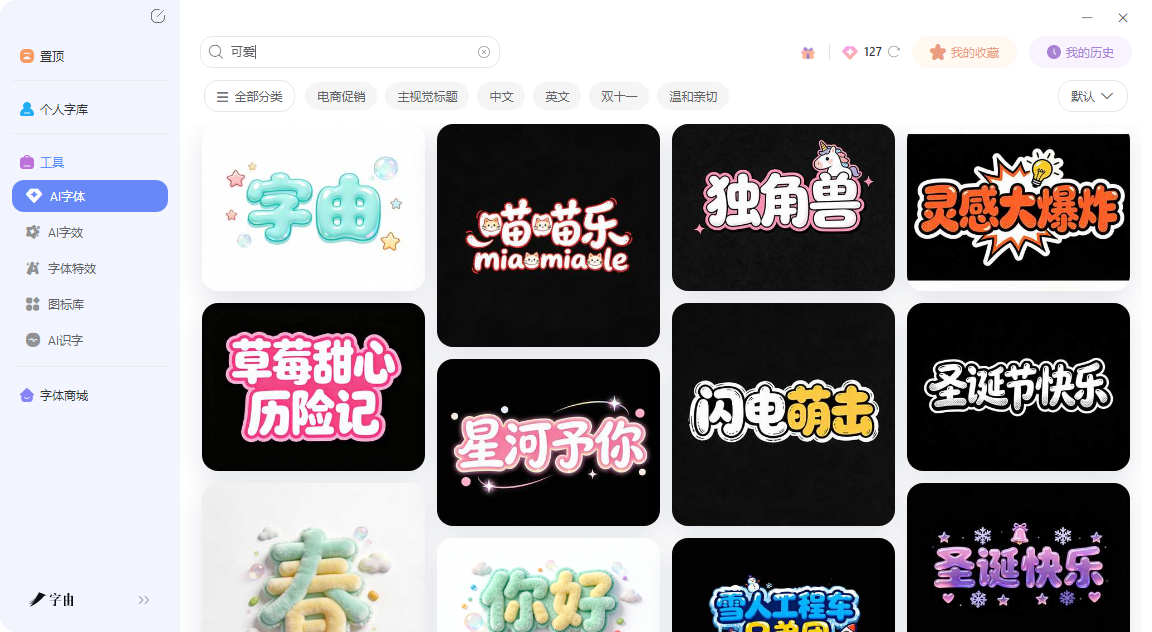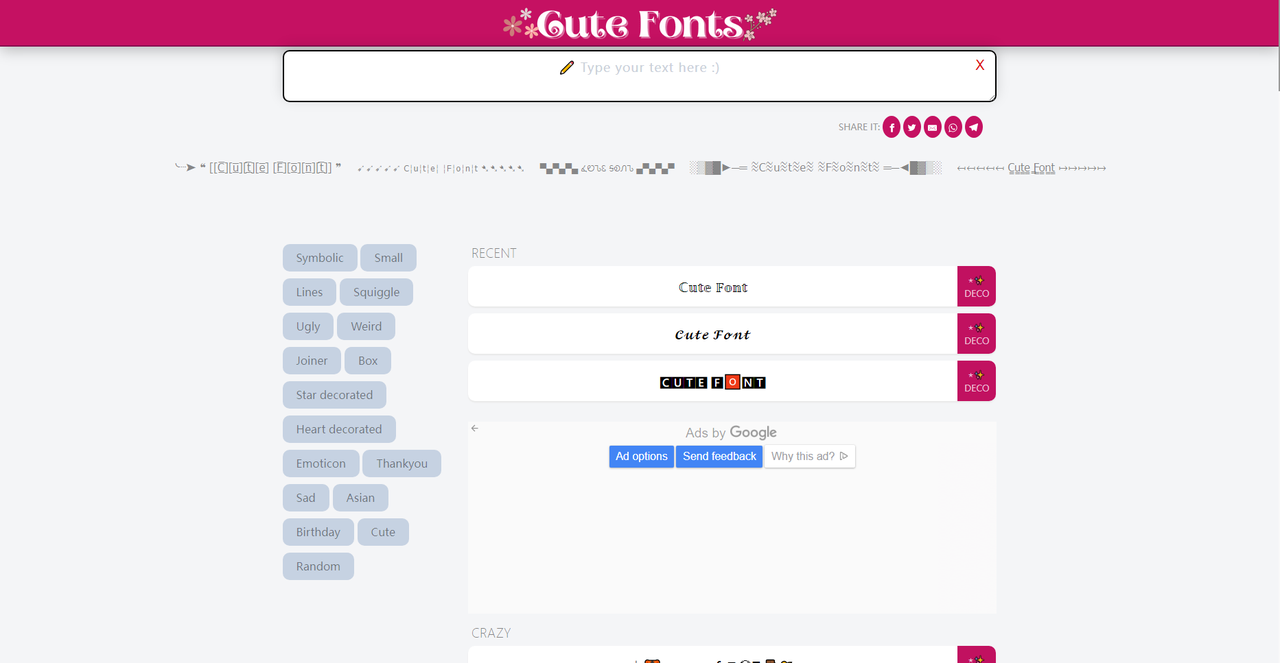
设计不够出彩?试试这些俏皮可爱的女生字体
做手账的时候,想给今天的心情配一行软萌的标题;给闺蜜做生日贺卡,希望名字带点少女心的装饰;设计甜品店菜单,字体要甜但不能腻。这些场景下,系统自带的黑体宋体是完全排不上用场的,这时候就需要专门做可爱风格的字体资源,从圆滚滚的手写体到带爱心、星星装饰的花体,从日系kawaii到软萌卡通。今天我就为大家整理了6个可爱女生字体相关的网站,有在线生成器、有下载站、有灵感合集,总有一款是你喜欢的。
做可爱风格设计,最常用的字体类型无非就那几样:圆体(拐角圆润)、手写体(有温度)、卡通体(带装饰)。字由的字体库里这三类加起来上百款,而且全都可以一键激活。打开字由客户端,在左侧“字体类型”筛选栏里,你可以同时勾选“圆体”“手写体”“创意字体”——这三个分类里藏着大量适合可爱风格的字体。比如“字由芳华体”,笔画纤细带连笔,像用彩色水笔写出来的,做手账标题特别出片;还有“点字青花楷”,虽然是楷书但圆润可爱,适合中式风格的可爱设计。
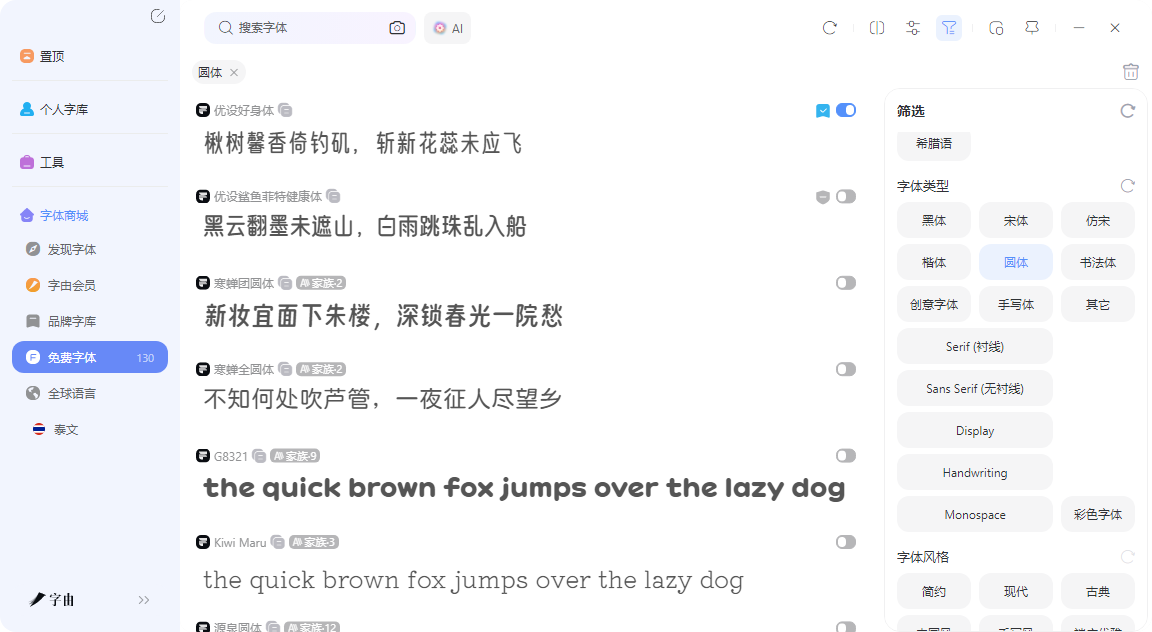
除此之外你也可以选择用字由的AI字体功能来生成图片模板,操作过程也十分简单,只需要点进【AI工具】,再搜索框里搜索“可爱”“粉色”等关键词,就可以出来很多类型丰富的、已经自己调好样式的AI字体模板,你只需要在文字框里填入你想要的文字,再等待几十秒就可以拥有现成的可爱的字体图片了,并且你也可以选择放在各种设计软件里,十分方便。
2、Gute Fonts
第二个网站叫Gute Fonts。它的界面很简洁:顶部一个输入框,输入文字后,下面会生成多种装饰风格的字体样式。其中最符合“可爱女生字体”需求的是“Heart decorated”(爱心装饰)和“Star decorated”(星星装饰)——每个字母周围会加上小心心或小星星,生成出来的文字像贴纸一样。还有“Cute Font”本身就是一个自带圆润感的样式。这个工具生成的是Unicode字符,不是图片。所以你选中喜欢的样式,点一下旁边的复制按钮,就能直接粘贴到微信朋友圈、抖音简介、小红书文案、游戏昵称里。不需要下载任何软件,打开网页就能用。如果你只是想偶尔给社交账号加点可爱元素,Gute Fonts比装字体快多了。
3、Cute Font Generator
第三个工具叫Cute Font Generator。从截图看,它主打“kawaii vibes”(可爱氛围),生成的文字会自带emoji装饰,比如🎨✨🕶️等。而且它提供了多种分类:Bold、Aesthetic、Cursive、Cute、Instagram等,每种分类下面又有若干样式。使用方式和上一个类似:输入文字,选择样式,复制粘贴。适合在Instagram、Discord、TikTok等社交平台上用可爱字体写简介、标题或评论区留言。这个工具的亮点是“随机”功能——你不太确定想要什么风格的时候,点一下随机,它会自动帮你组合一种样式,有时候能撞到意想不到的效果。
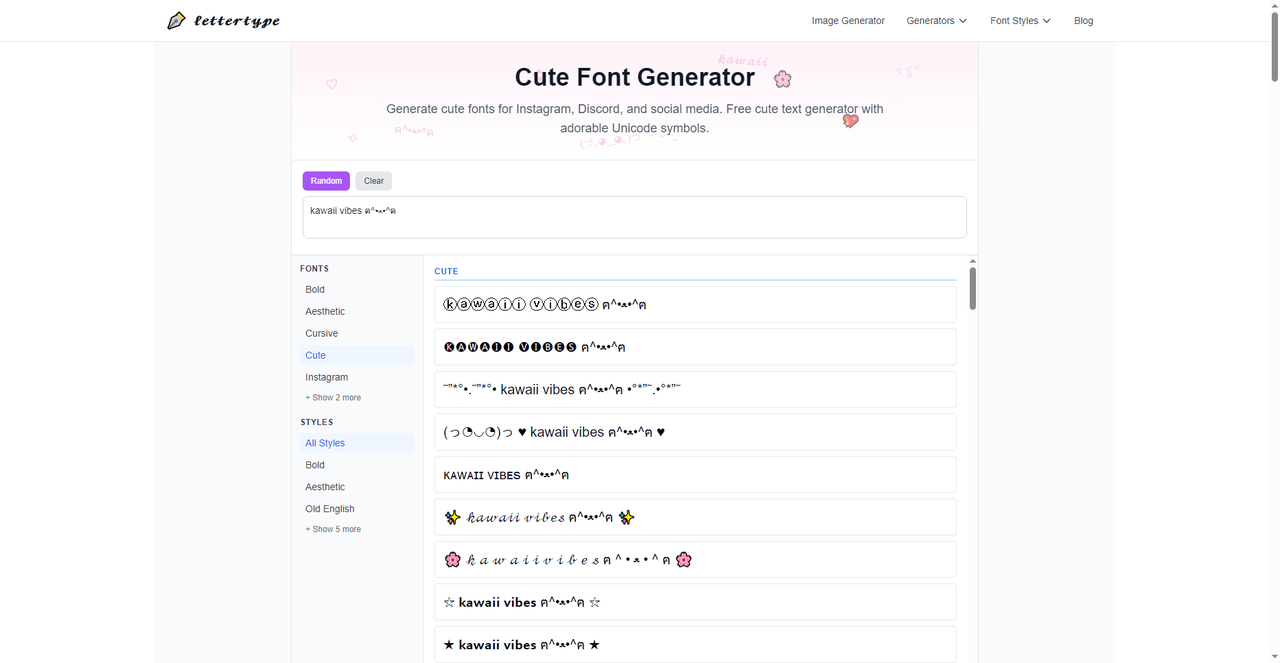
4、Kawaii Fonts
第四个网站叫Kawaii Fonts。这是一个专门收集日系可爱字体的下载站,标题写着“39 free fonts”,收录了Kinkee、Billo、Kitten(5种样式)、Cupid de Locke、Cookies等字体。每款都有预览图,展示了字母和简单单词的效果。“Kawaii”是日语的“可爱”,这类字体通常笔画圆润、带点手绘感,有的还会在字母上加小圆点或者小尾巴。截图中“Kitten”字体的预览写的是“Kitten Bold Regular AaBbCcDdEeFf”,看起来是软萌的猫主题字体;“Cookies”像饼干一样圆圆胖胖的。
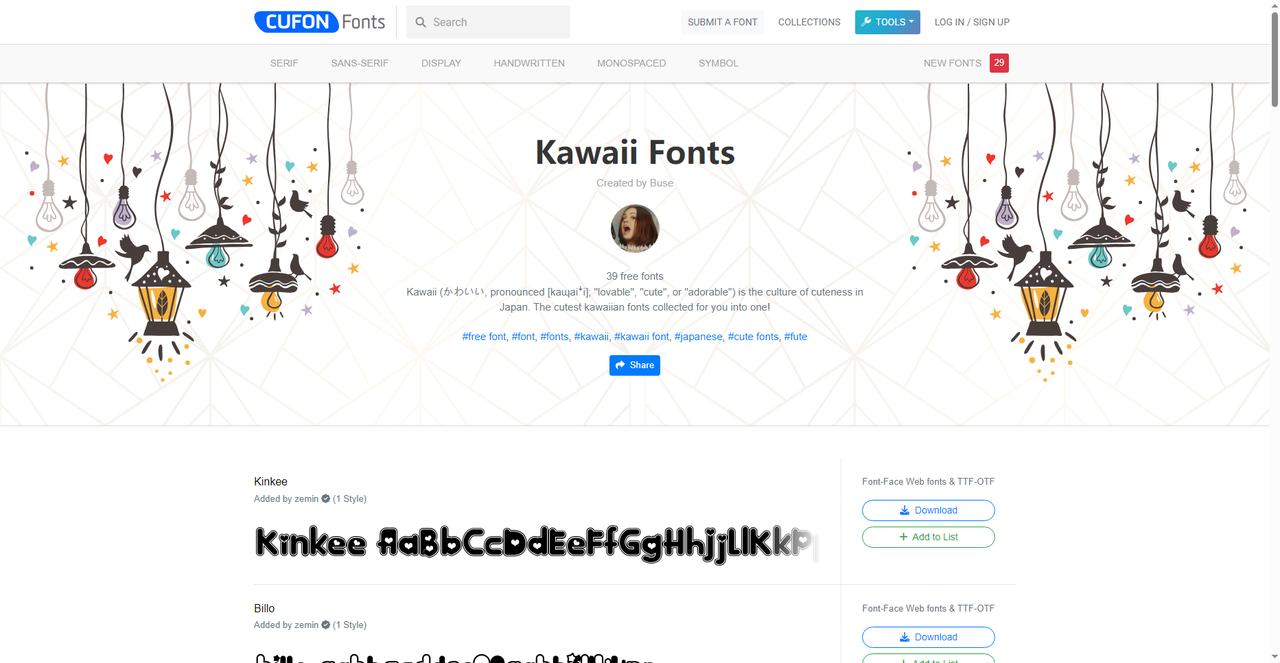
5、cutefonts
第五个网站是CuteFonts.org。从截图看,它提供了多种装饰风格的字体预览,分类详细。它的核心功能是“CUTE & PRETTY TEXT GENERATOR”——输入文字后,下面会列出各种样式的预览,每个样式旁边有“SHARE IT”按钮,可以直接复制或分享。样式包括Cursive Font(草书)、Super Bend(超级弯曲)、Double Struck(双线体)、Medieval Font(中世纪)、EmojiFont(表情符号字体)、Tribal Font、Old English等。这个站的装饰风格更偏“花哨”——有的样式会在字母周围加框、加符号,适合做派对邀请函、社交媒体配图、或者需要强烈视觉效果的标题。
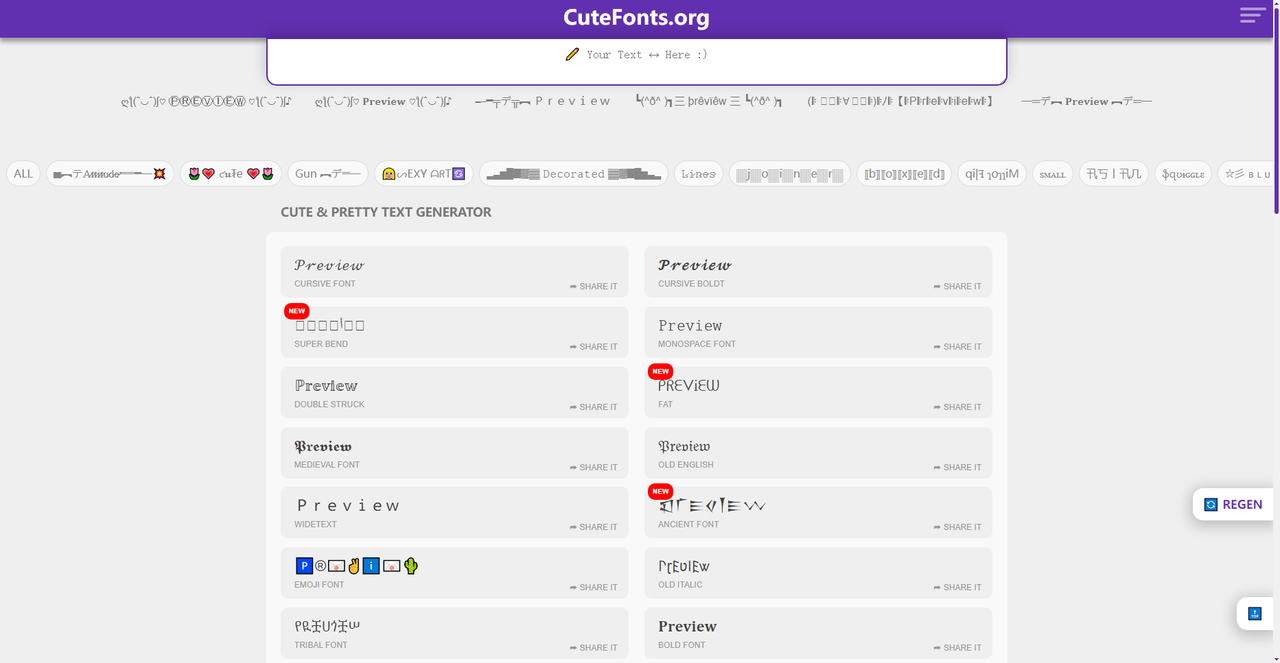
可爱女生字体的来源其实不少,关键看你用在什么地方。字由最适合设计师在PS、Word里长期使用,圆体、手写体、卡通体一键激活,免费商用筛选让你不用担心版权,云端同步换电脑也不怕;Gute Fonts和Cute Font Generator适合普通用户快速给社交账号加可爱元素,在线生成复制粘贴,不用装任何东西;Kawaii Fonts提供大量可下载的可爱字体文件,适合需要安装到电脑上做设计的人;那这篇文章则是灵感来源,不知道用什么字体的时候翻一翻,可以直接抄作业。